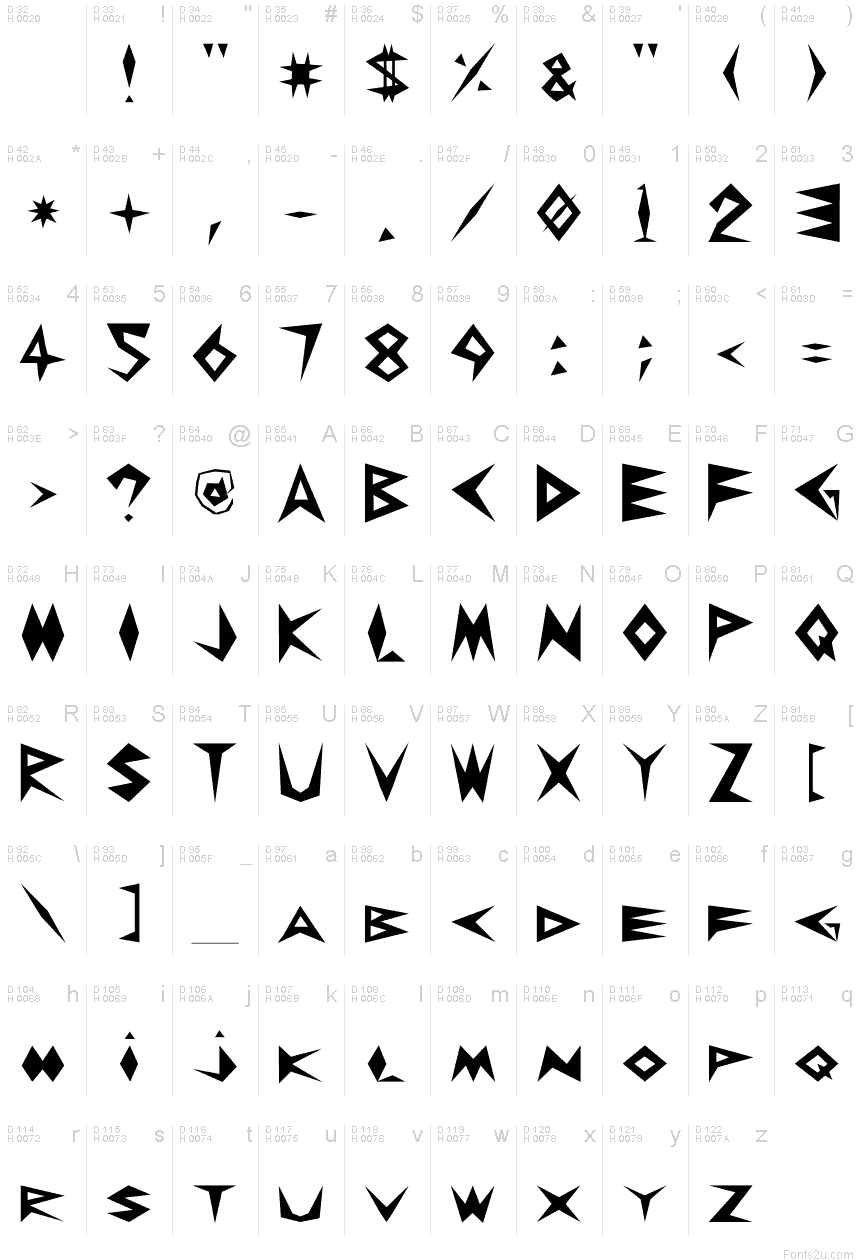
Triangularity 是由 Compufix Systems 开发的一款免费的棱角分明、带有扭曲感的显示字体,呈现出一种锋利、近乎卢恩字母(runic)的独特风格。大写字母由坚硬的楔形和三角形切角构成,使即便常见的字母看起来也显得紧张、尖锐,且带有刻意的动荡感。
这使得这款免费字体非常适合用于游戏 Logo、科幻海报、俱乐部传单、专辑封面以及需要呈现破碎感和合成感的标题设计。它同样适用于简短的标题和字母组合,因为其陡峭的斜线和类似箭头的分裂造型,无需过多字符即可迅速营造强烈的视觉冲击力。